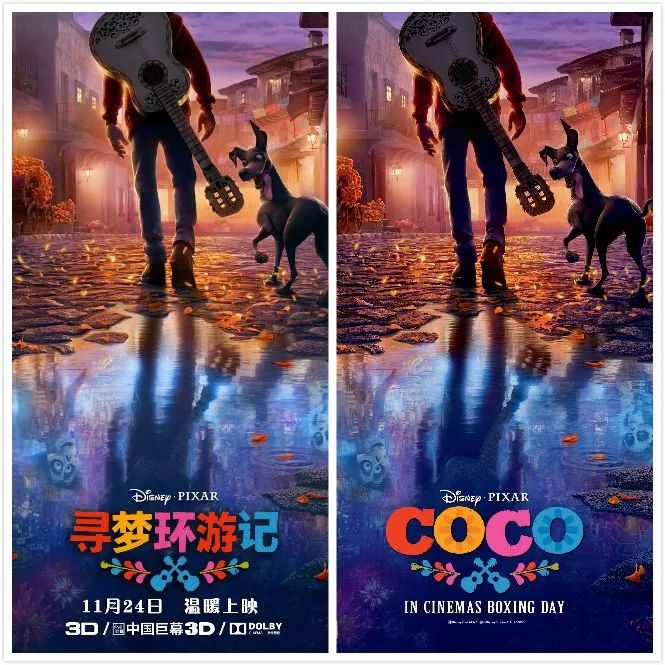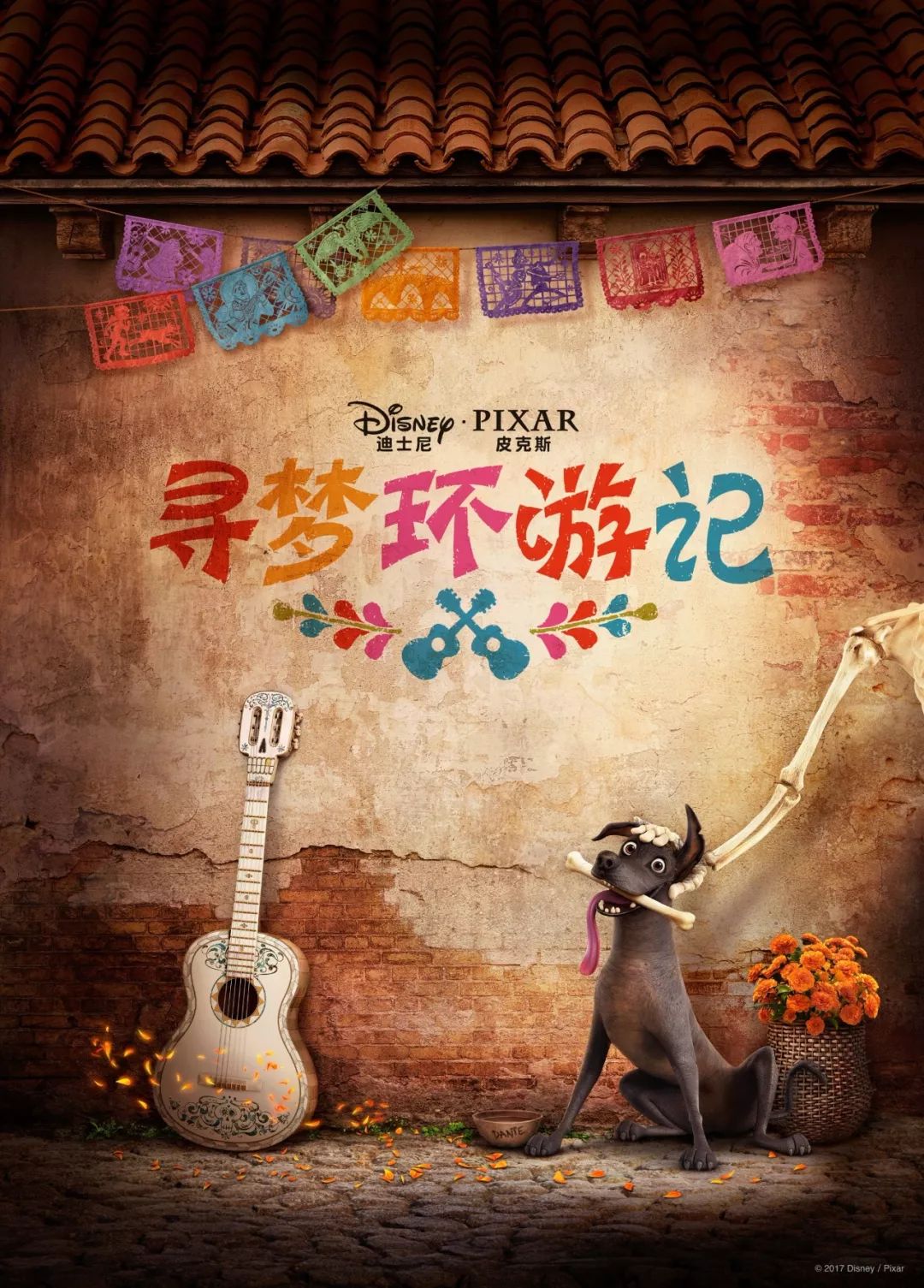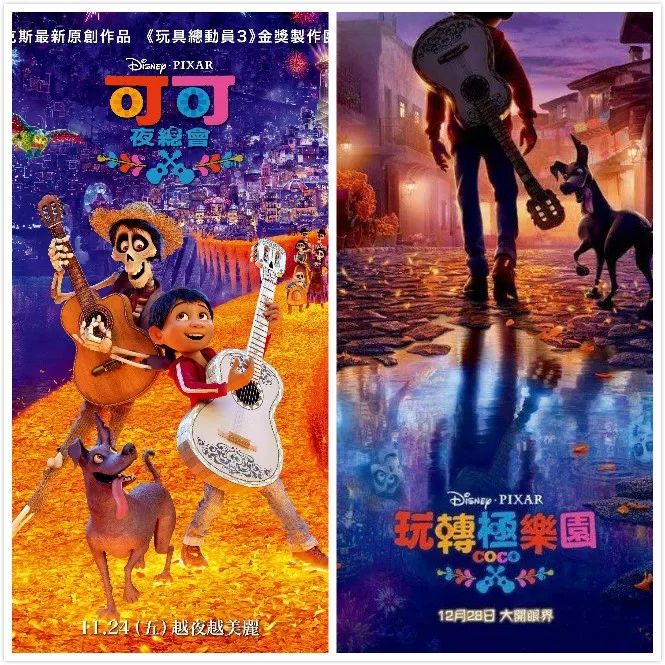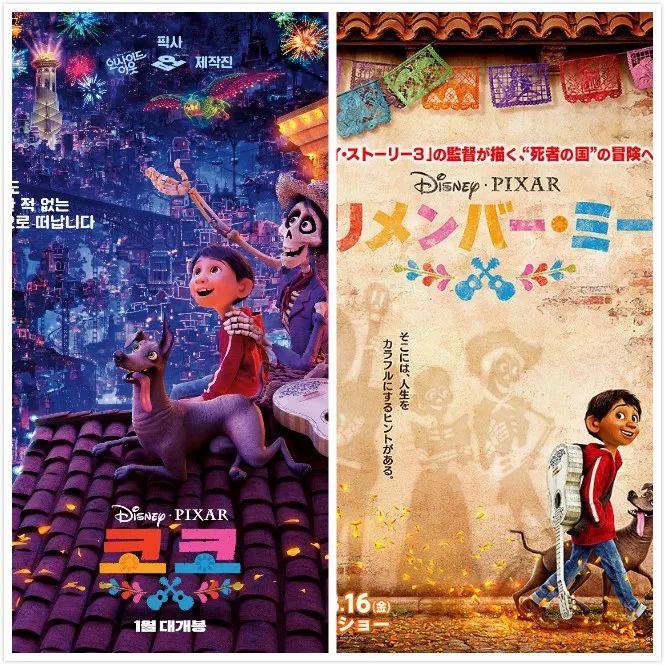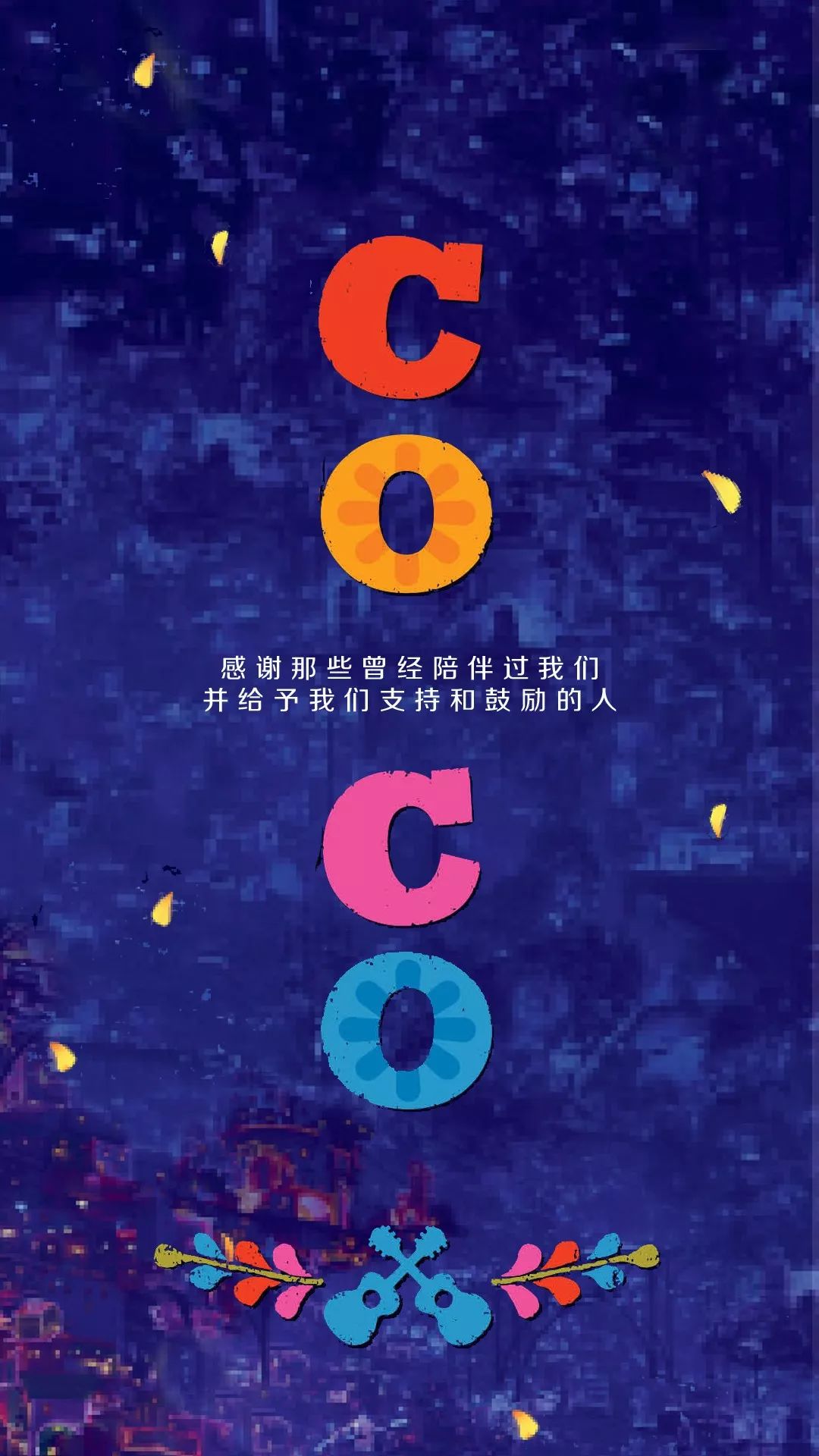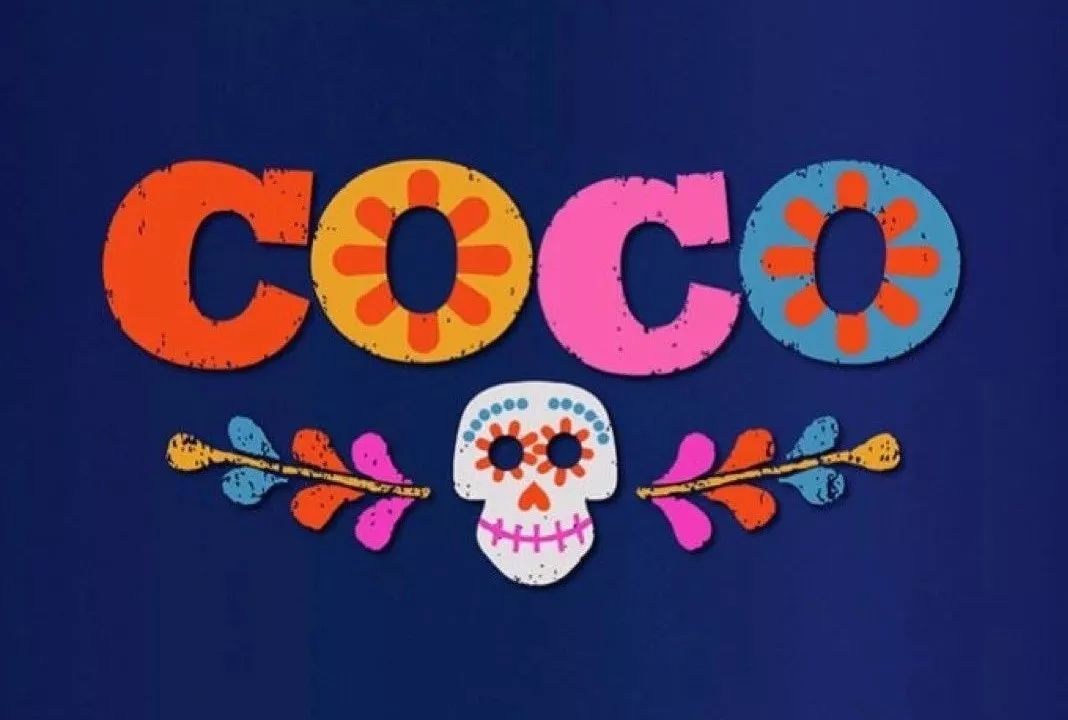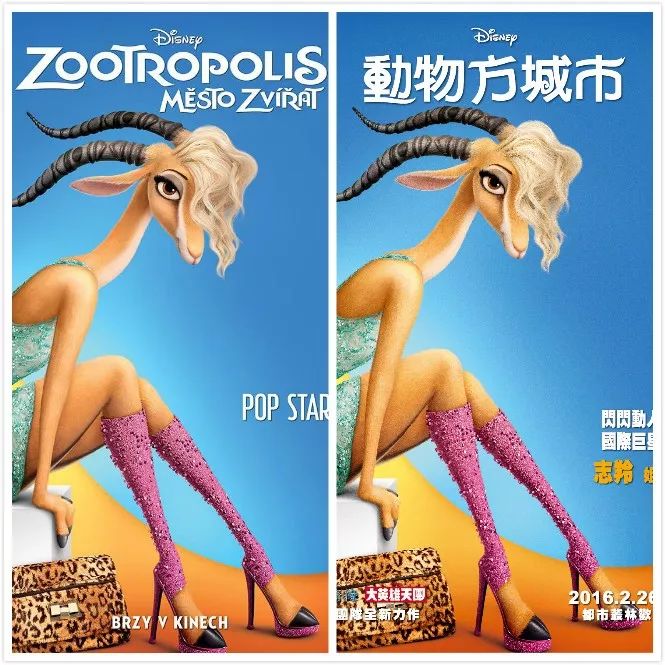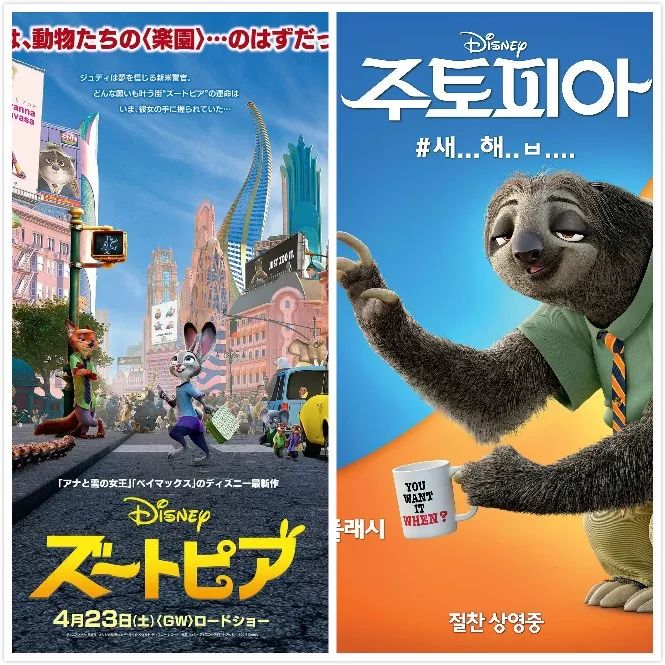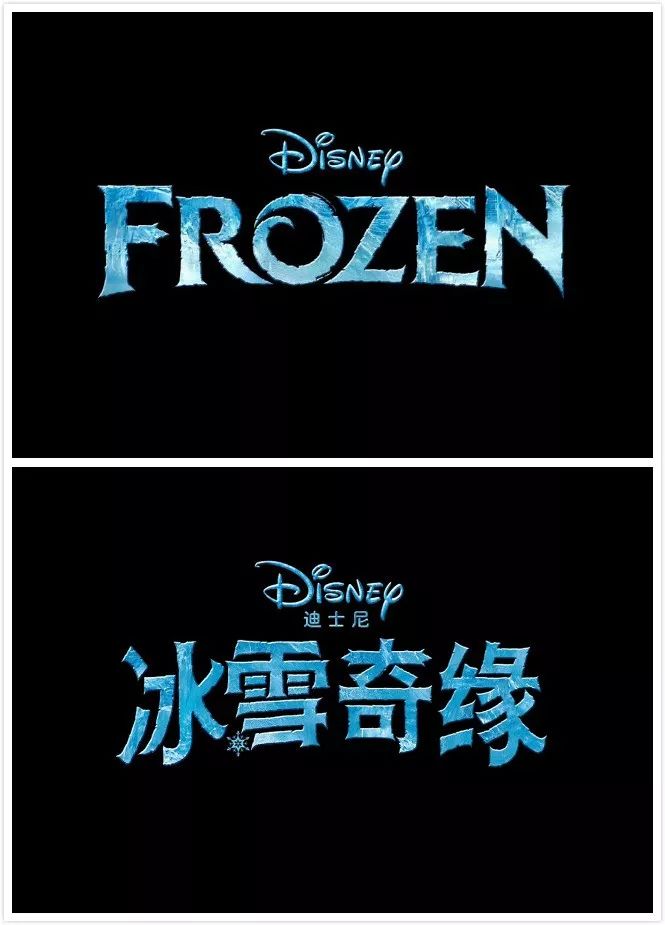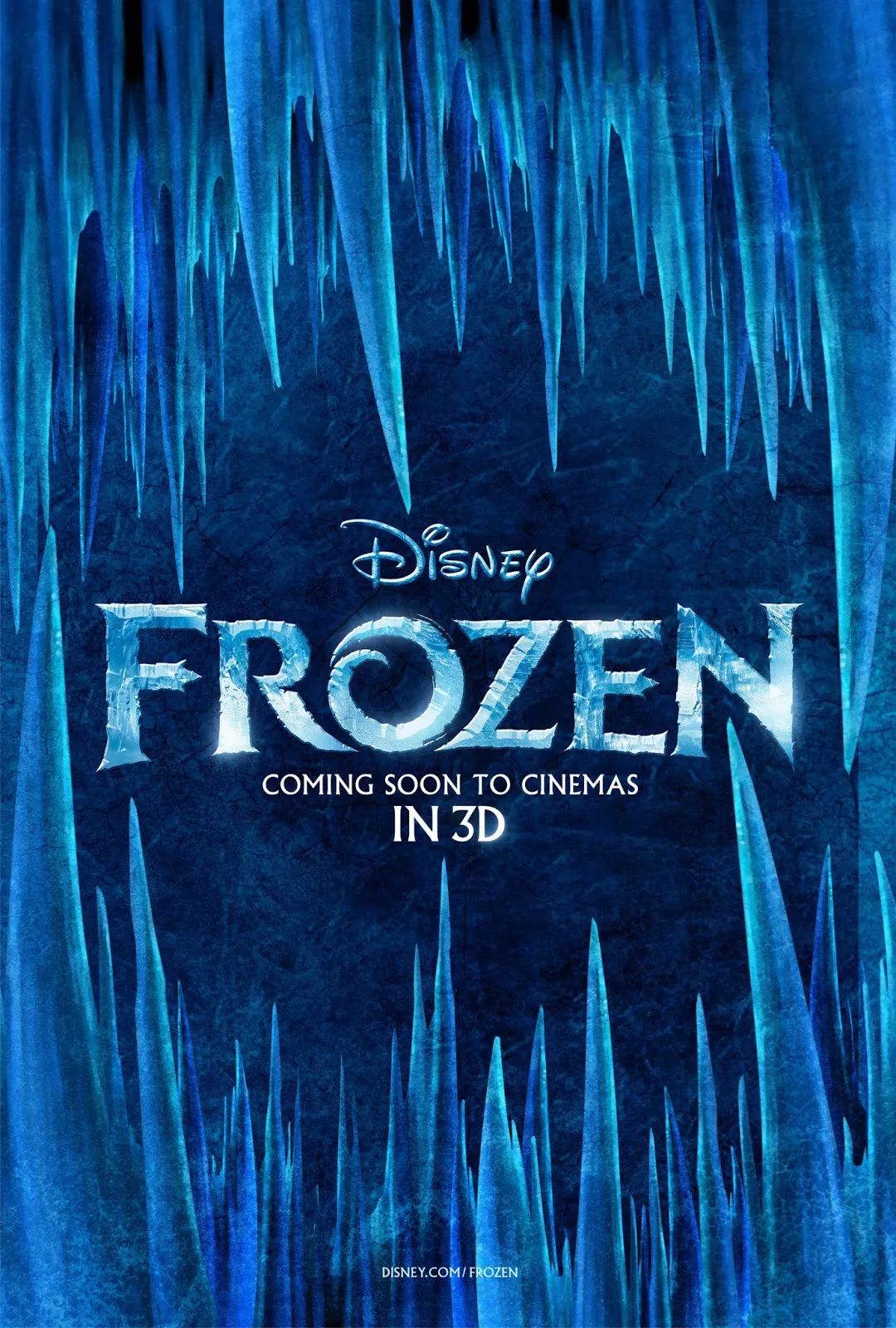
动画电影字体设计案例分享,一大波动画电影字体,正在等你翻牌子
最感动的《COCO》
时间拉回一年前,柚子记得是在一个深夜去的,看之前一直告诉自己不要哭,后来发现眼泪还是不听使唤。最可怕的是,身边的男同胞,也在发抖般地抽泣,现在想起来的,浑身还会起鸡皮疙瘩(全身一酸)~
确实完全戳中了我的软肋,特别是太奶奶唱歌那一段,很难不想起自己的亲人,所以他在豆瓣上的评分非常高,我觉得都可以10分。
估计差的那一分,都是被名字耽误了,我真的很想吐槽一下,什么寻梦环游记,是觉得五个字读起来顺吗?
看看豆瓣上的评论,都无语了,还有微软雅黑,是什么鬼,没钱买字体版权吗?
不是啊,预告片的海报字体都好看点,只是依然没有融合性。
看看人家台湾,香港的,片名虽然沙雕,但至少人家字体融合了些许英文,看到那个圈圈没?另外科普一下,台湾喜欢把墓地称为夜总会,而香港更是什么电影都爱加个“极”字。
同为亚洲国家,日本韩国就很注重内涵,韩国是直译过来的,코코就是COCO,日本是用的歌曲名“Remember me”,而且都吸取了英文字体的精髓。
竖着排也很好看,你可以把这张图存下来当壁纸,不过后面也会给你的,哈哈!
《疯狂动物城》打开新世界
这部动画片,柚子也超喜欢看,头一次觉得兔子和狐狸可以这么配,树懒可以这~么~可~爱~
比coco早一年,豆瓣评分却比它还高,可能小动物,总能让人爱心泛滥吧。
中文字体跟英文字体简直一模一样,看起来就很“浪”。
不过这回轮到吐槽台湾版了,动物方城市什么鬼?看完我真的方了。
日韩依然没让人失望,日本版加入了兔耳朵元素,看着就很卡哇伊,而韩国版下面那堆省略号,跟闪电真是神契合。
网红《冰雪奇缘》
要说最火爆迪士尼动画,非《冰雪奇缘》莫属了,大家小巷都是那首《let it go》,各种舞台剧、文化衍生品,甚至是妆发,都是大小朋友的最爱。
豆瓣评分虽然略低,但依然不妨碍它大火,这都五年了,艾莎依然是红人。
中文虽然模仿了英文字体,还加了一个小雪花的设计,但边缘的抖动还是处理得不细致。
放大看看,是不是这样,就“奇”字那学了点“E、F”,有点偷懒了吧。
韩国版就基本上还原了英文字体的精髓,即使没怎么加效果。
日本的迪士尼乐园那么火,怎么可能少得了它,不过这次它完全跳脱了英文的抖动,走的是女王style。
香港、台湾看起来差不多,除了香港把“冰”改成“魔”外,边缘化也没有韩国弄得好,感觉不是“抖”,是“裂”,哈哈!
哈哈!所以看来看去,还是英文字体最好看了,上字由,搜索ice ,第二个、第三个都是啦~